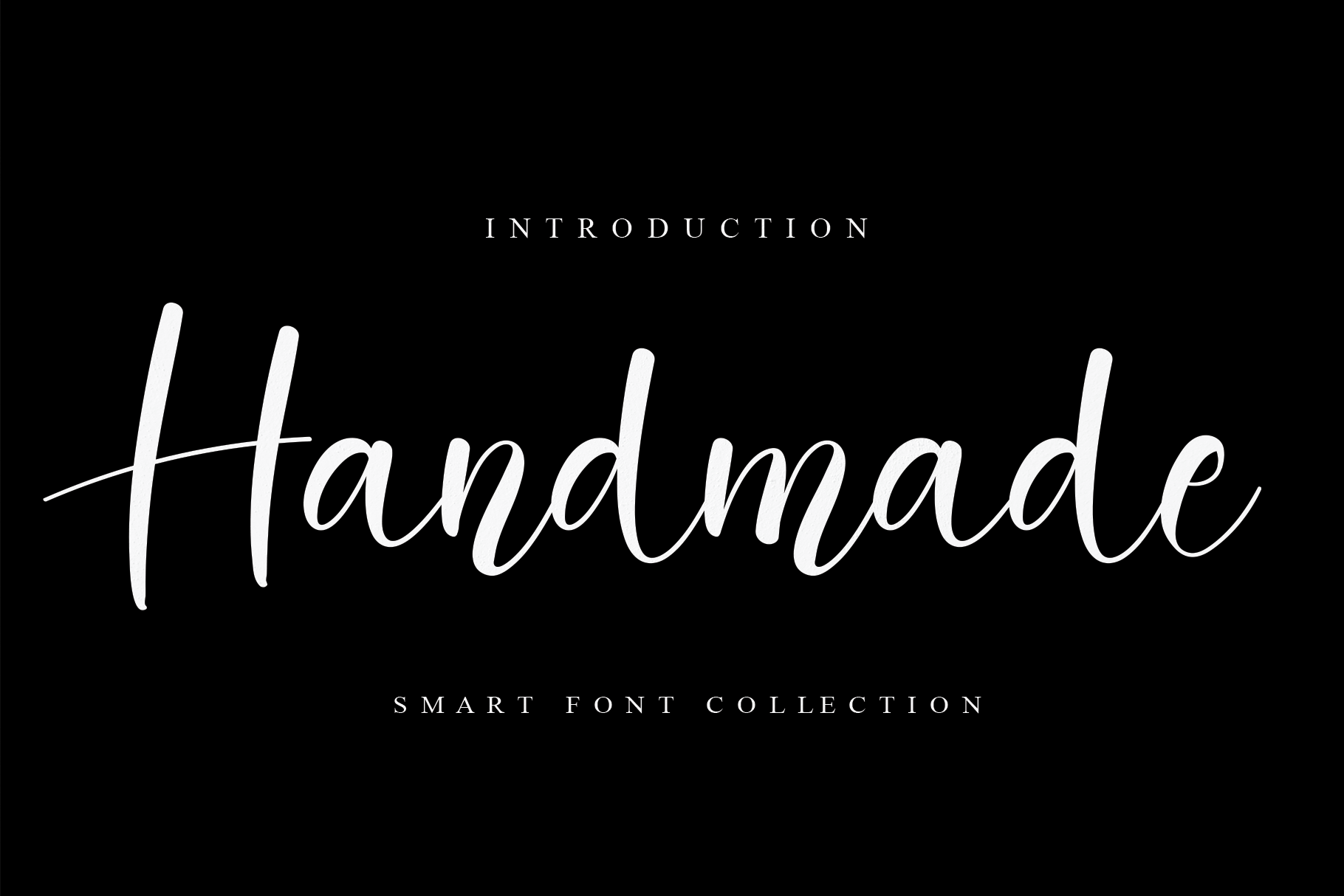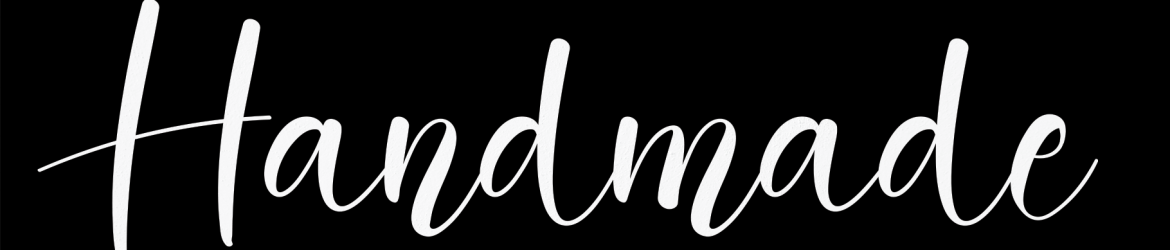
Handmade Typeface – Download Grátis
A Handmade Typeface é uma fonte cuidadosamente criada com um toque de elegância, projetada especialmente para aqueles que desejam dar vida às suas ideias criativas. Seja você um designer de perfil social ou um entusiasta do xilográfico em DIY, esta fonte mágica transforma qualquer conceito em uma verdadeira obra de arte. Perfeita tanto para as redes sociais como para projetos pessoais, a Handmade Typeface é o elo faltante entre ideias e realidade. Seja você uma artista ou um entusiasta de design, esta fonte será sua melhor parceira em todas as suas missões de criação visual.